CSS Nite LP61のブースから
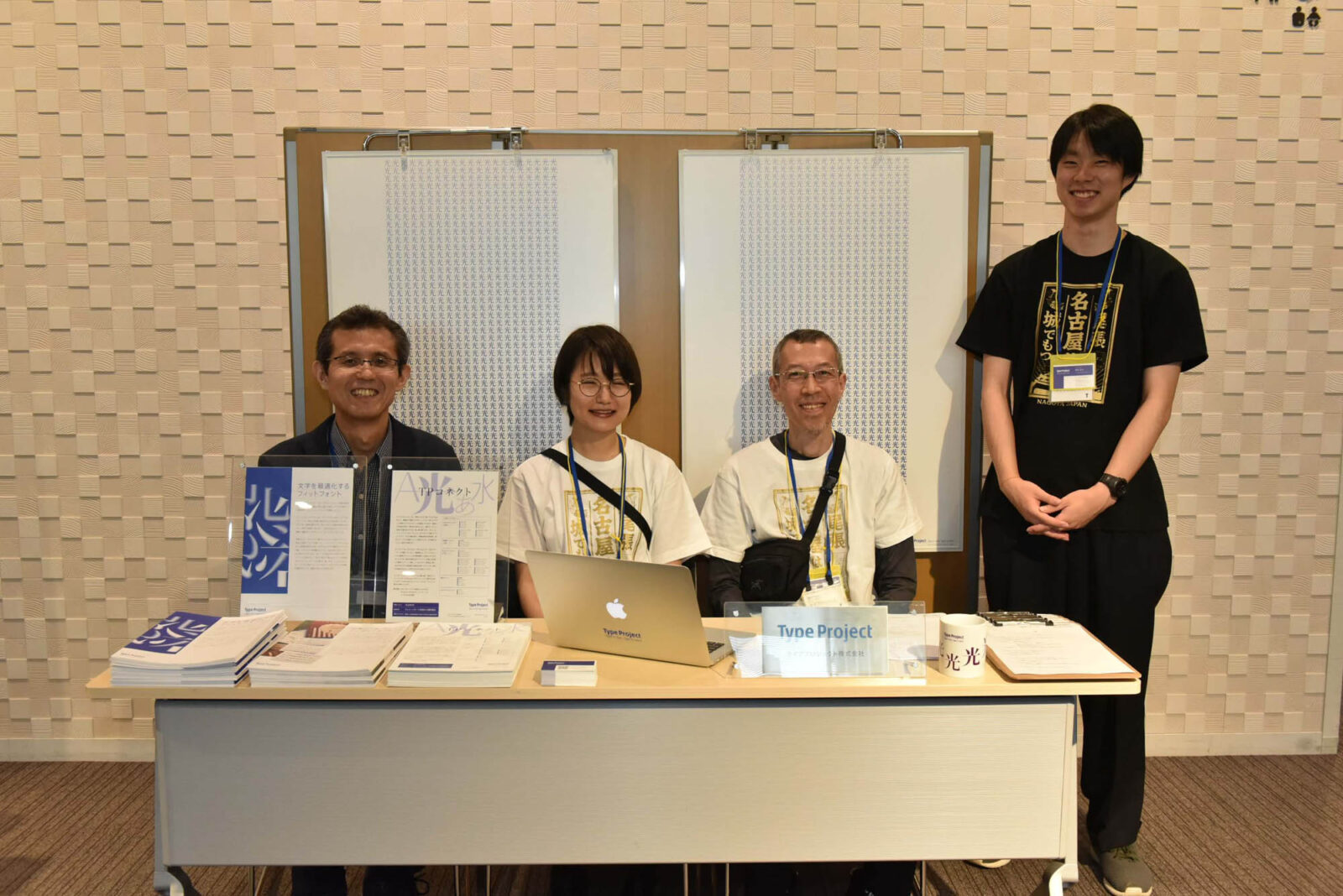
タイププロジェクトは、2019年5月18日に開催されたCSS Nite LP61「これからのフォントとウェブでの組版を考える日」の展示ブースに出展しました。CSS Nite LP61は、フォントを「作る人」と「使う人」が触れ合うとのできるイベントとして企画されたもので、ウェブデザイナー、フォントベンダー、Webフォントサービスのプロバイダー、企業の広告・広報担当者など、200人を超える参加者が集まりました。
セッション前半は、“フォントおじさん”関口浩之さん(ソフトバンク・テクノロジー)の基調講演からはじまり、松田直樹さん(まぼろし)がWebフォント活用のノウハウを、鷹野雅弘さん(スイッチ)が、ウェブコンテンツでの組版について語りました。
セッション後半は、新進気鋭の書体デザイナーによるクロストークからスタート。越智亜紀子さん(フォントワークス)、山田和寛さん(nipponia)、木龍歩美さん(砧書体制作所)、吉田大成さん(アドビ)が、現在までにかかわったプロジェクトや、今後の展望などについてプレゼンテーションしました。最後のセッション、藤田重信さん(フォントワークス)による「筑紫書体のこれまで、と、これから」は、90分におよぶもので、開発の裏話も含め、筑紫書体シリーズのコンセプトと変遷が語られました。
タイププロジェクトの展示ブースでは、鈴木功に加え、タイプデザイナー2名、タイプエンジニア1名が、参加者の皆さまとお話ししました。ブース壁面にはフィットフォントのパネルを展示し、ノートPCでは、タイププロジェクトの年間定額プランであるTPコネクトや、リニューアルしたばかりのサイトをご紹介しました。
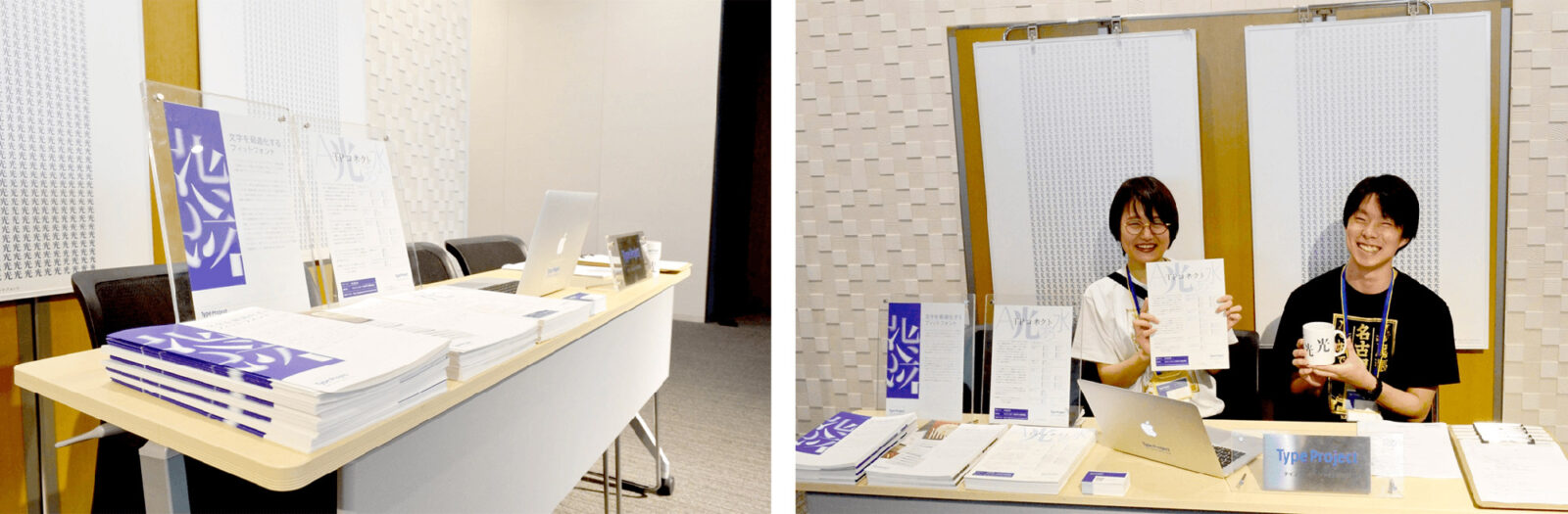
とくにサイト内のフィトフォントのページでは、欧文フォントにあわせて日本語フィットフォントのウエイト、字幅、コントラストをスライドで調整する作業を、皆さまに実際に体験していただきました。鈴木功みずからがスライドを動かしながら説明するシーンもありました。
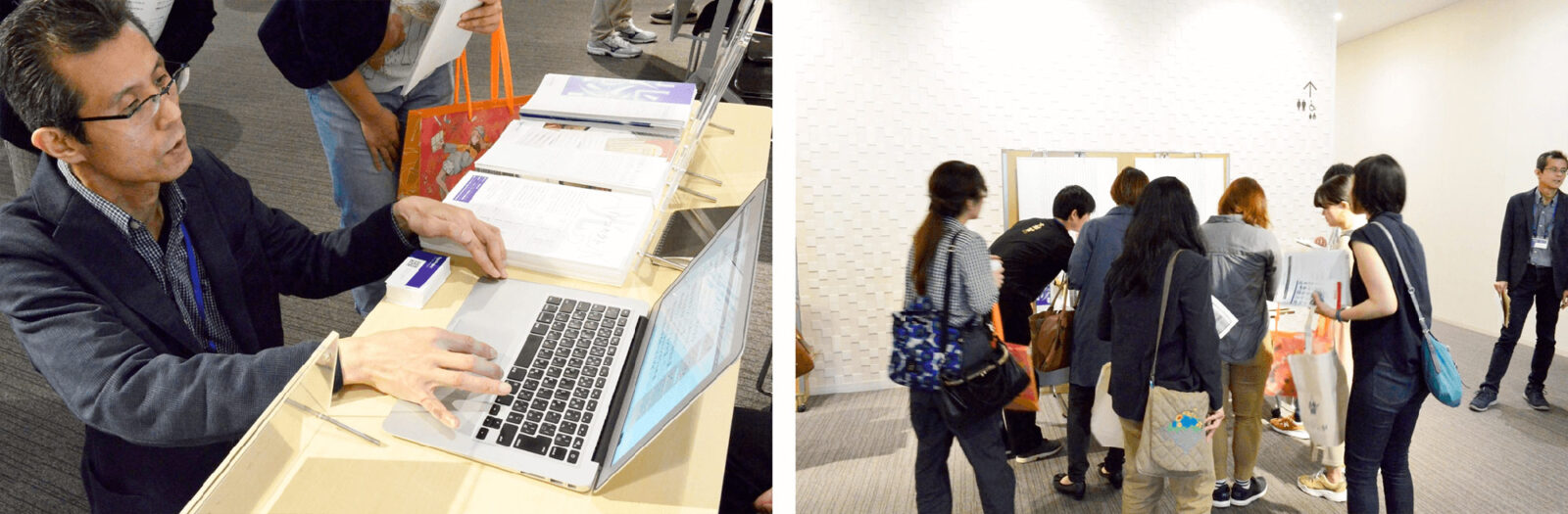
タイププロジェクトが提供した「DENSO TP 2017」が、松田直樹さんのセッションで代表的なコーポレートフォント事例として紹介されたこともあり、何人もの方から、コーポレートフォントの資料についてのお問い合わせをいただきました。また、現在かかわっているブランディングのプロジェクトで、フィットフォントを提案してみたいという方もいらっしゃいました。
Q. フィットフォント技術を使ったコーポレートフォント事例には、どんなものがありますか?
セッションでもご紹介いただいたデンソーのプロジェクト(https://typeproject.com/interviews/interview20171115)のほかに、さくらインターネット(https://typeproject.com/interviews/interview20171002)、アルピーヌ(https://typeproject.com/interviews/interview20170523)などの例があります。
Q.(スタッフが着ている金シャチフォントTシャツを見て)そのTシャツは何ですか?
わたしたちは、都市のイメージをフォントにする「都市フォント」というプロジェクトを推進しています。金シャチフォントはその一環で、鈴木功の出身地である名古屋のフォントを作り、地元で育て、世界へ発信しようという試みです。今日わたしたちが着ているのは、その金シャチフォントを使ったTシャツです。
Q.タイププロジェクトって、何の会社なんですか?
書体をデザインし、フォントとして提供する会社です。AXIS Font、TP明朝、TPスカイなど、次世代標準を目指したベーシックなフォントを世の中に送り出しているほか、会社のブランディングを促進するコーポレートフォントを得意としています。また、都市のアイデンティティを表現する都市フォントにも取り組んでいます。